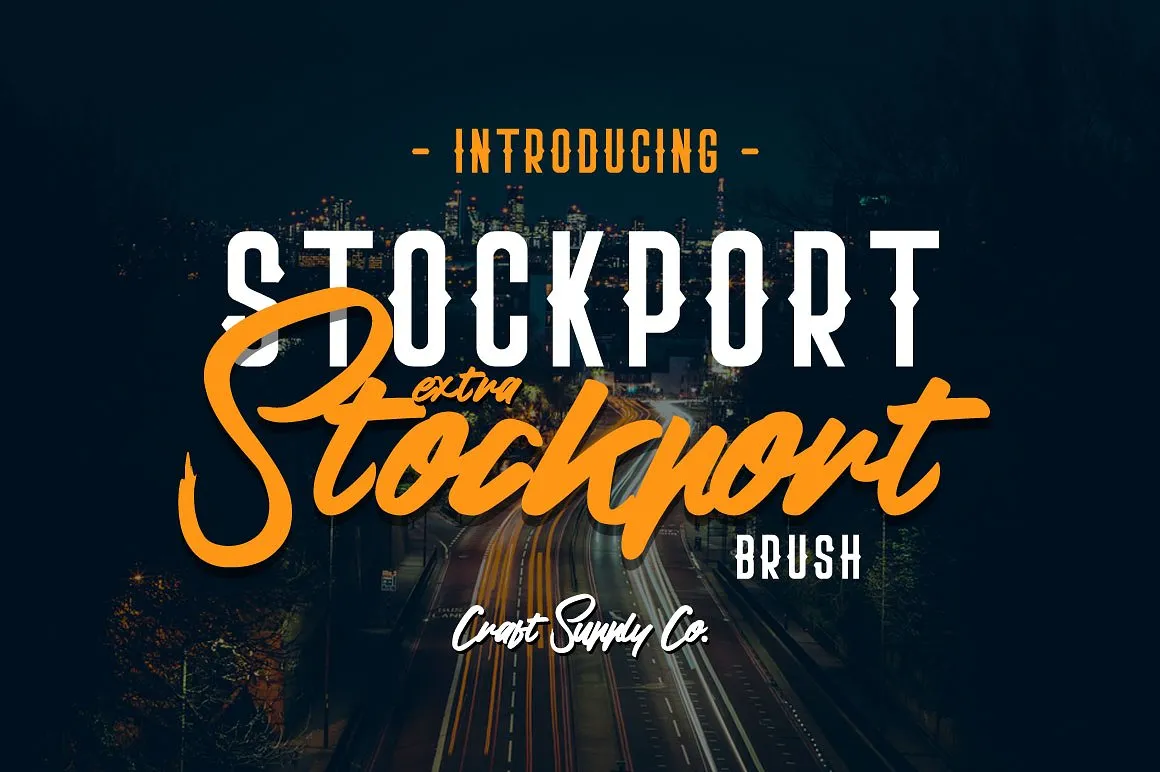
Stockport Font Family – Download Grátis
Introduzimos Stockport Extra & Brush! Desenvolvida pelo 178-MC, essa é uma fonte premium disponível na CreativeMarket. Agora, para oferecer ainda mais valor aos nossos clientes, você pode baixar esta fonte gratuitamente hoje. Stockport Extra & Brush combina um estilo de tipo gótico sem serif com elementos de tipo script brush em um só design, criando uma sensação única e moderna. Perfeito para diversas aplicações gráficas, como logotipos, cartões de agradecimento, declarações pessoais, branding, cartas de convite, posters ou qualquer projeto artístico que você esteja desenvolvendo, seja ela um conceito criativo e inovador ou uma arte tradicional. Além disso, seu estilo casual como design a mão dura ou com temas de águacolor também se encaixa perfeitamente em trabalhos DIY, design de livros ou até mesmo no estilo vintage pop.